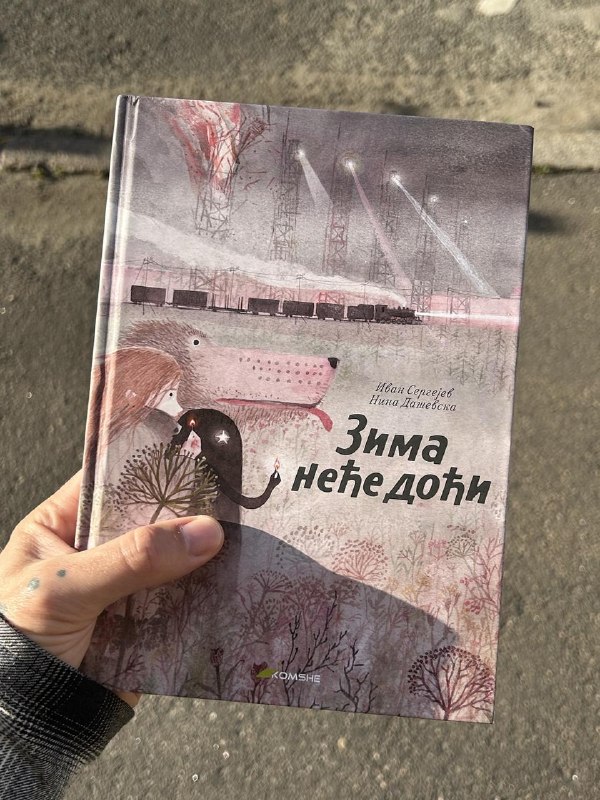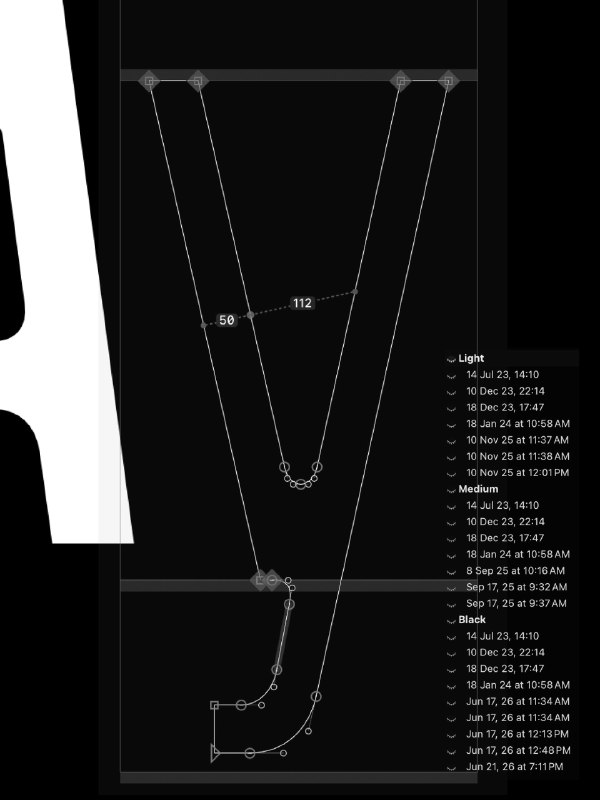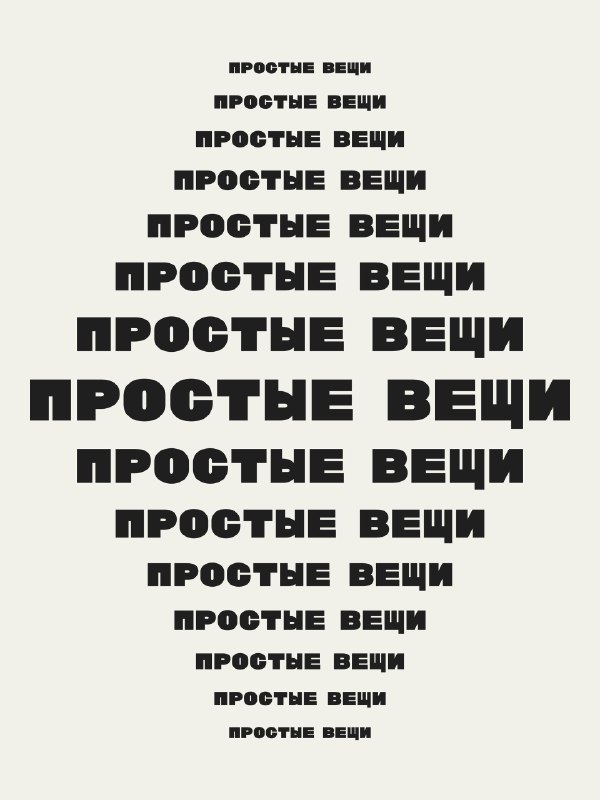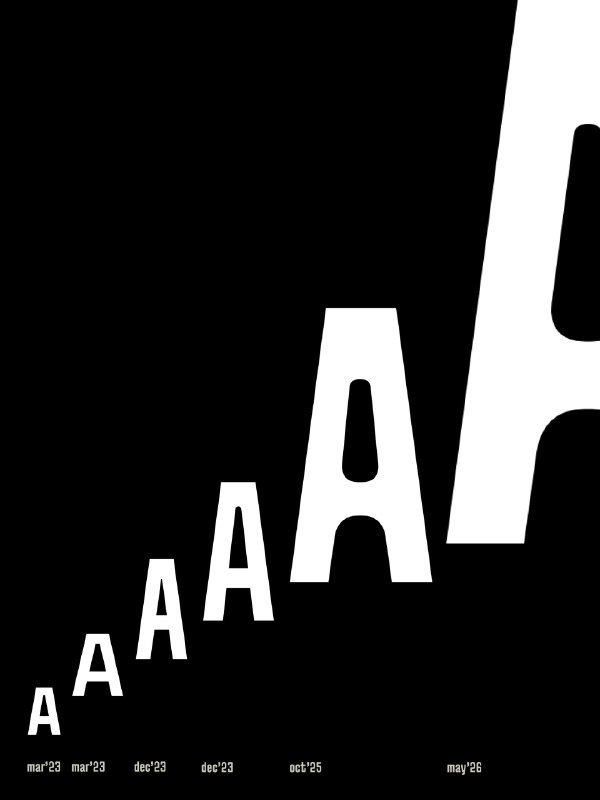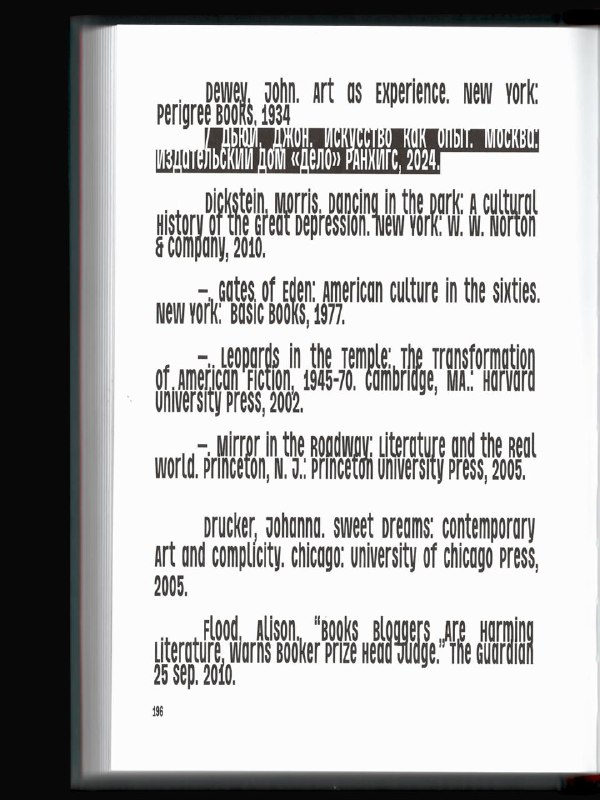
фа-фа-фа
шрифт с огоньком (шутка шрифтовика за 300)
Nada in use
Зин Metamorphosis
Идея основана на исследовании живого и неживого, а также трансформации и цикличности — того, как один и тот же объект снаружи может быть похож на другой, оставаясь при этом совершенно иным по своей сути.
Зин напечатан на ткани, в нём собраны мои фотографии из поездки в Японию.
Дизайн: Полина Овчинникова
Шрифт: FAT Nada
Обновили логотип любимых OMUT. За приглашение спаcибо Umwelt Office.
Получили сербское издание книги «Зимы не будет» с нашим леттерингом и кастомным шрифтом на обложке. Такое очень приятно держать в руках.
Шрифт и леттеринг: Лиза Островская и Федя Аброськин
Первый серьезный релиз в новом составе FAT: нарисовали логотип для нового бренд-медиа сервиса Ясно.
«Всё сложно» — журнал о том, как справляться с реальностью. Мы сразу влюбились в нейм и концепцию про право быть неудобными и сложными. Нарисовали кучу вариантов — колких, динамичных, немного запутанных, неидеальных, странных и интересных, как сама жизнь (которая такова, какая есть, и больше никакова !!).
Лучший вариант теперь живет в шапке журнала. Гордимся собой и благодарны за кайфовое сотрудничество с командой Ясно.